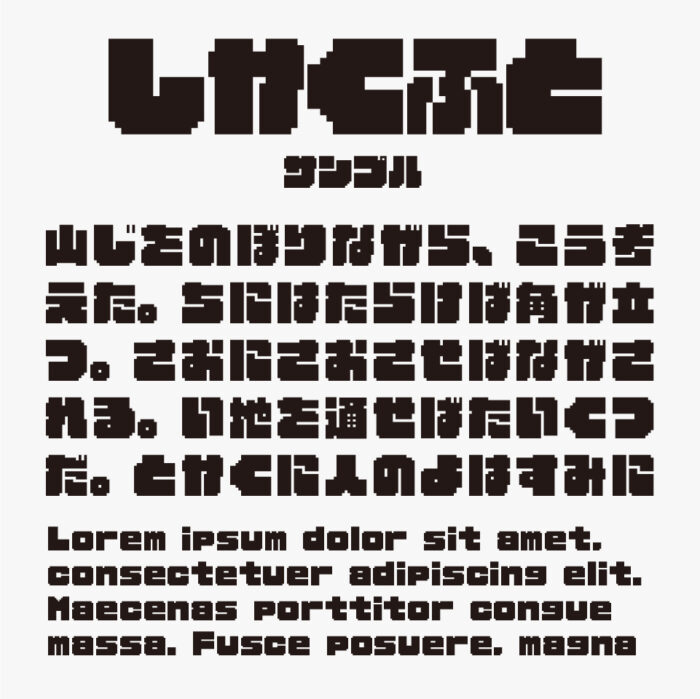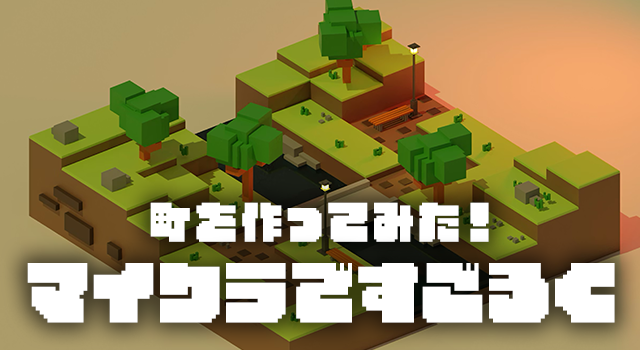
しかくふとフォントは、ブロックを削って作られたような重厚さと直線的なシルエットが特徴のデザインフォントです。
ピクセルフォントののような角ばったデザインと均一な極太さが、インパクトのある力強さある表情がとってもステキなフォントです。
文字同士のまとまりが高く、視認性も確保されているため、ポップな印象を与えながらもドドーンとインパクトがあるので、サムネイルや見出し・ロゴにもぴったりなフォントです。